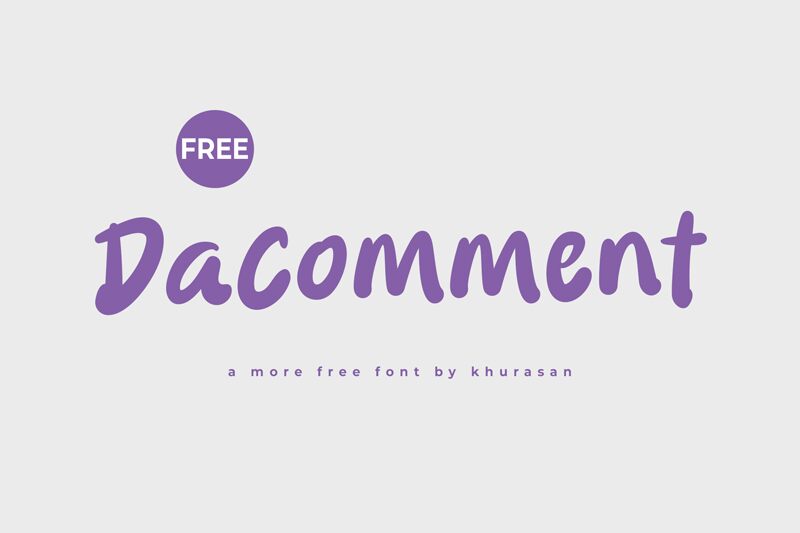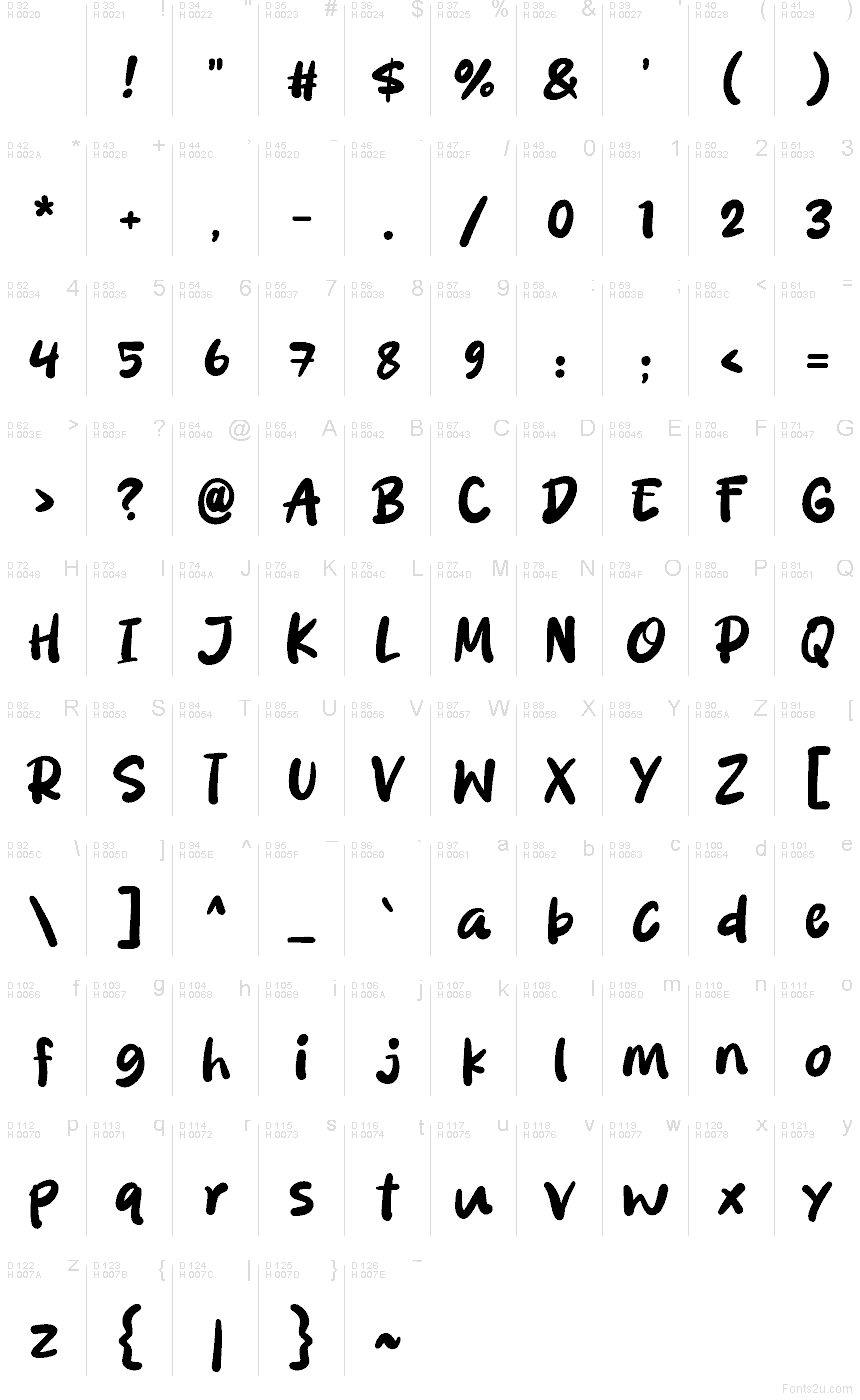
Dacomment od Khurasan to darmowy, rysunkowy font typu display, wyróżniający się grubą, ręcznie rysowaną linią. Litery opierają się na miękkich, przypominających pociągnięcia pędzla krzywych oraz pękatych, zaokrąglonych łączeniach. Dzięki temu całość sprawia wrażenie niezobowiązującego komiksowego pisma, które wygląda raczej jak szkic niż dopracowany projekt.
Świetnie sprawdzi się na opakowaniach, plakatach dla dzieci, w menu kawiarni, miniaturach na YouTube czy zabawnych grafikach do mediów społecznościowych, wszędzie tam, gdzie darmowy font ma budować ciepło, a nie stawiać na sterylną geometrię. Użyj go do krótkich nagłówków, tytułów czy brandingu w stylu naklejek – pękaty rytm i lekko nieregularny charakter sprawiają, że nawet kilka słów nabiera życia w mgnieniu oka.